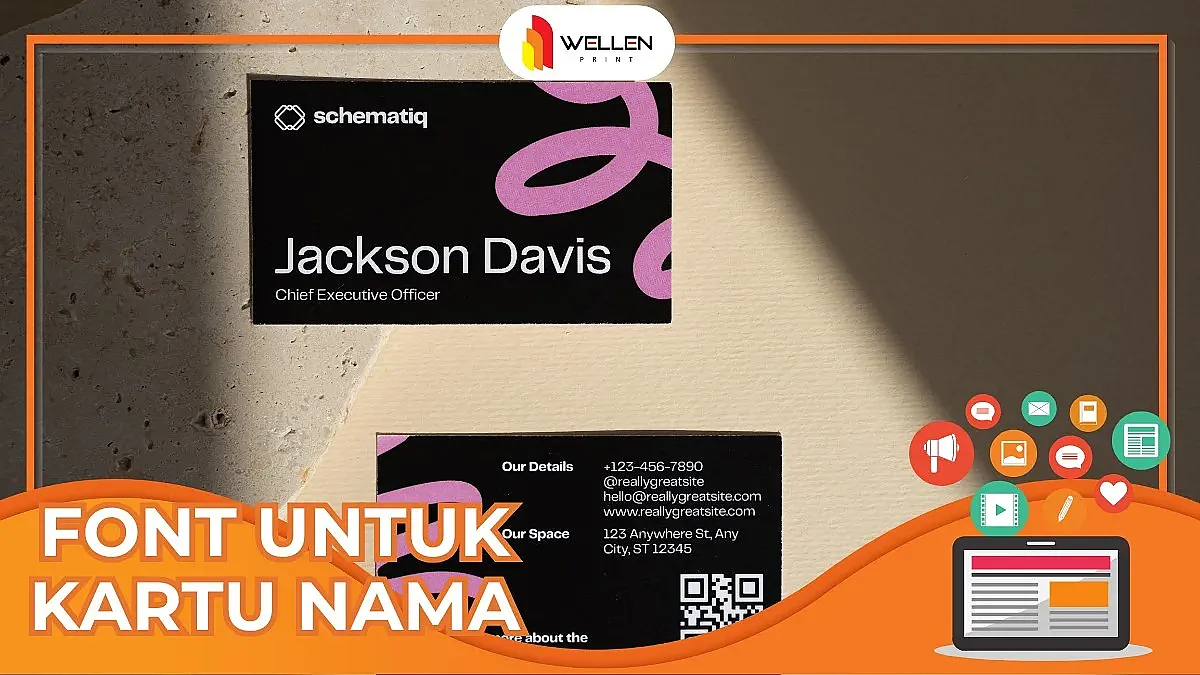
Font untuk Kartu Nama, Kunci Identitas Profesional
Kartu nama memiliki peranan krusial sebagai representasi citra profesional pribadi maupun mewakili suatu merek dalam bentuk mini. Ruang terbatas dari kartu nama membuat Anda wajib menata desain dan elemen pendukung secara cerdas agar memuat cukup informasi tanpa terasa sesak. Salah satunya dengan memilih font untuk kartu nama yang pas.
Font sering dianggap perkara sepele dalam pembuatan kartu nama. Padahal, masing-masing tipografi mempunyai karakteristik berbeda yang memengaruhi kesesuaian aplikasinya. Seperti ketebalan, model goresan, dan keterbacaan wajib menjadi bahan pertimbangan agar kartu nama Anda tampak profesional dan kredibel. Rekomendasi font untuk kartu nama yang bisa Anda pilih dijabarkan lengkap di sini!
TogglePertama, ada kelompok font kartu nama yang menampilkan citra profesional dan modern, yang didominasi oleh kelompok font sans-serif, antara lain:
Helvetica merupakan salah satu font yang paling banyak digunakan pada industri desain. Keluarga sans-serif yang diciptakan tahun 1957 ini tak lekang oleh waktu karena terkenal dengan garis dengan proporsi seimbang sehingga menghasilkan goresan yang bersih dan keterbacaan sangat baik. Helvetica cocok untuk menuliskan informasi panjang maupun pendek di kartu nama.
Montserrat menjadi rekomendasi jenis tipografi berikutnya yang memiliki keterbacaan baik di berbagai ukuran font kartu nama. Keluarga sans-serif geometris ini mencitrakan goresan yang lebih modern dan ramah dibandingkan sans-serif lainnya. Ketersediaan berbagai ketebalan huruf membuat fleksibilitas penggunaannya lebih luas, mulai dari kartu nama untuk industri startup hingga industri kreatif.
Beralih ke Lato yang termasuk dalam keluarga sans-serif humanis yang dalam Bahasa Polandia berarti “musim panas”. Font ini memang dibuat untuk menyeimbangkan sentuhan profesional dan personal dalam satu bingkai, jadi tidak terlalu kaku seperti keluarga sans-serif umumnya.
Keterbacaannya juga baik, bahkan dalam ukuran kecil, jadi bisa untuk menuliskan detail informasi di kartu nama. Lato cocok untuk menjadi font berbagai macam bisnis, mulai dari korporat hingga organisasi nirlaba, yang ingin menampilkan citra profesional namun tetap mudah didekati.
Raleway berasal dari sans-serif elegan dengan goresan khas di beberapa hurufnya, seperti W dengan persilangan di tengah dan L yang memiliki ekor panjang. Ketebalannya bervariasi, sehingga menciptakan kesan berbeda. Cocok menjadi pilihan font berbagai ukuran kartu nama dari industri fashion, desain, teknologi, dan sejenisnya yang ingin tampil artistik dan modern.
Futura berasal dari keluarga yang sama dengan Montserrat, yaitu sans-serif geometris. Font ini termasuk salah satu jenis tipografi tertua, ada sejak tahun 1927. Goresan klasik dari garis-garis geometris dan konsisten menjadi ciri khas sekaligus kekuatannya hingga tak lekang oleh waktu.
Tingkat keterbacaan Futura juga sangat baik, tidak kalah dengan font yang lebih baru. Cocok untuk kartu nama berbagai industri yang menekankan inovasi dan berpemikiran maju agar terus dapat beradaptasi dengan perubahan zaman. Bisa untuk industri otomotif, hiburan, fashion, dan banyak lagi.
Bila Anda ingin membuat kartu nama dengan sentuhan yang lebih personal tapi tetap elegan dan tampak profesional, maka beberapa jenis font serif dan script berikut bisa menjadi pilihan:
Playfair Display merupakan font untuk kartu nama dari keluarga serif transisional sehingga goresannya tidak terlalu kaku dan dibubuhkan bulatan pada ujung beberapa hurufnya. Playfair Display merupakan interpretasi dari gaya penulisan profesional yang modern dan mewah.
Kartu nama dari industri mode, kecantikan, seni, maupun bisnis yang menyasar kelas atas paling sesuai untuk menggunakan font ini. Namun, untuk menjaga proporsi ruang, sebaiknya Playfair Display dipadukan dengan font serif lain dan hanya dipakai untuk menonjolkan penulisan nama atau jabatan.
Baskerville juga sama seperti Playfair Display, dari keluarga serif transisional. Font yang hadir sejak pertengahan abad ke-18 ini semula difokuskan untuk penulisan buku dan media publik kelas atas. Sebab, goresannya menampilkan citra mewah dengan keterbacaan superior sehingga dikhususkan untuk kelompok tertentu saja.
Namun, seiring perkembangan zaman, penggunaan Baskerville menjadi lebih umum. Meskipun demikian, tidak mengurangi apalagi menghilangkan kesan profesionalisme dan otoritas di dalamnya. Sehingga, font ini sangat cocok untuk bahan kartu nama premium dari praktisi hukum, akademisi, maupun konsultan senior yang ingin menonjolkan kredibilitasnya.
Pacifico merupakan script bernuansa retro yang cukup tebal, tapi estetik, sehingga kuat sekali citra kreatif dan inovatif yang dipancarkan bila menggunakannya untuk kartu nama. Font ini sendiri sangat populer dan banyak digunakan untuk berbagai kebutuhan lain.
Namun, Pacifico lebih cocok untuk penulisan informasi pendek karena memakan ruang dan tingkat keterbacaannya rendah. Cocok untuk kartu nama desainer grafis, fotografer profesional, dan pengusaha kuliner.